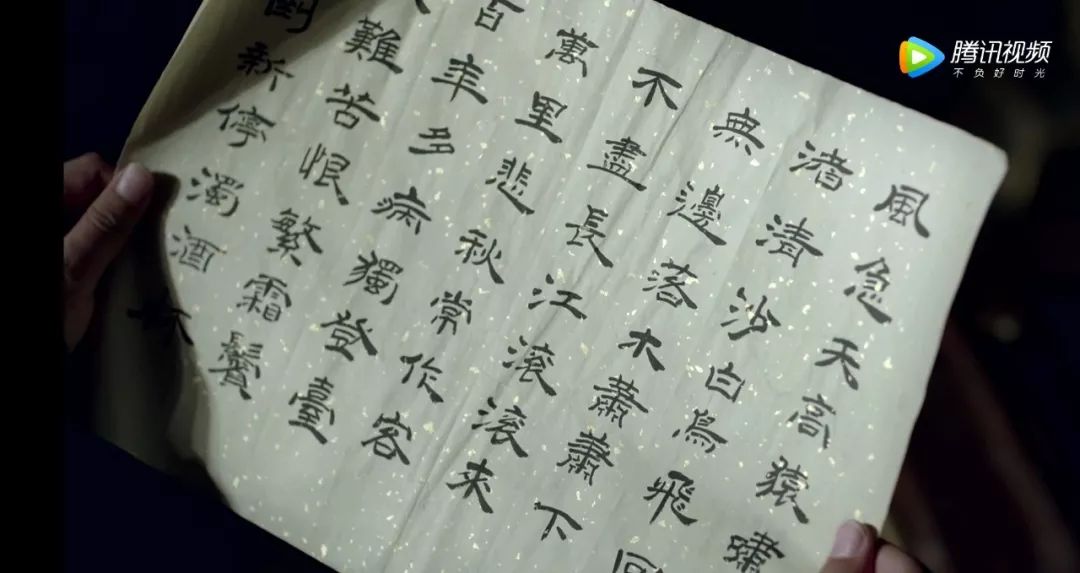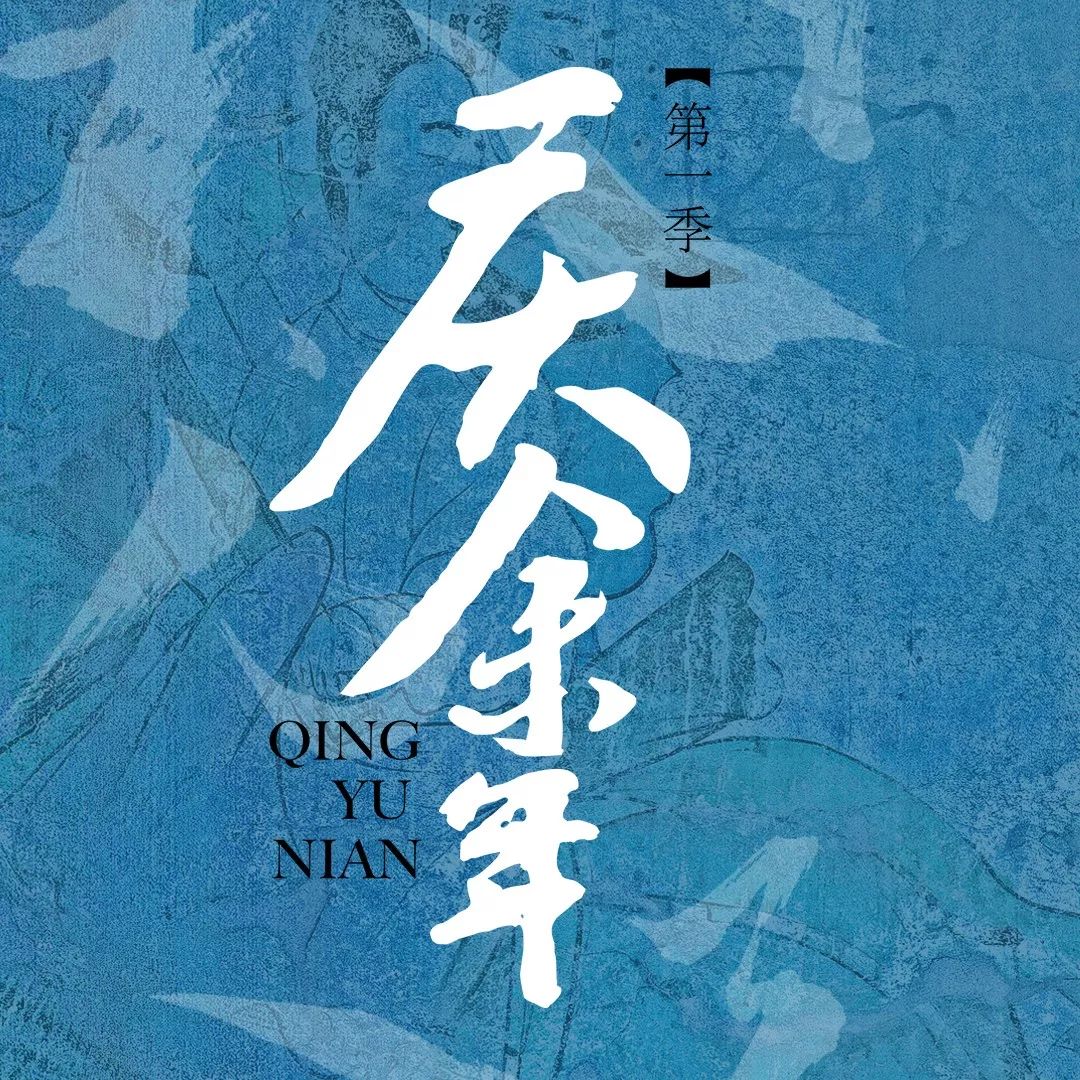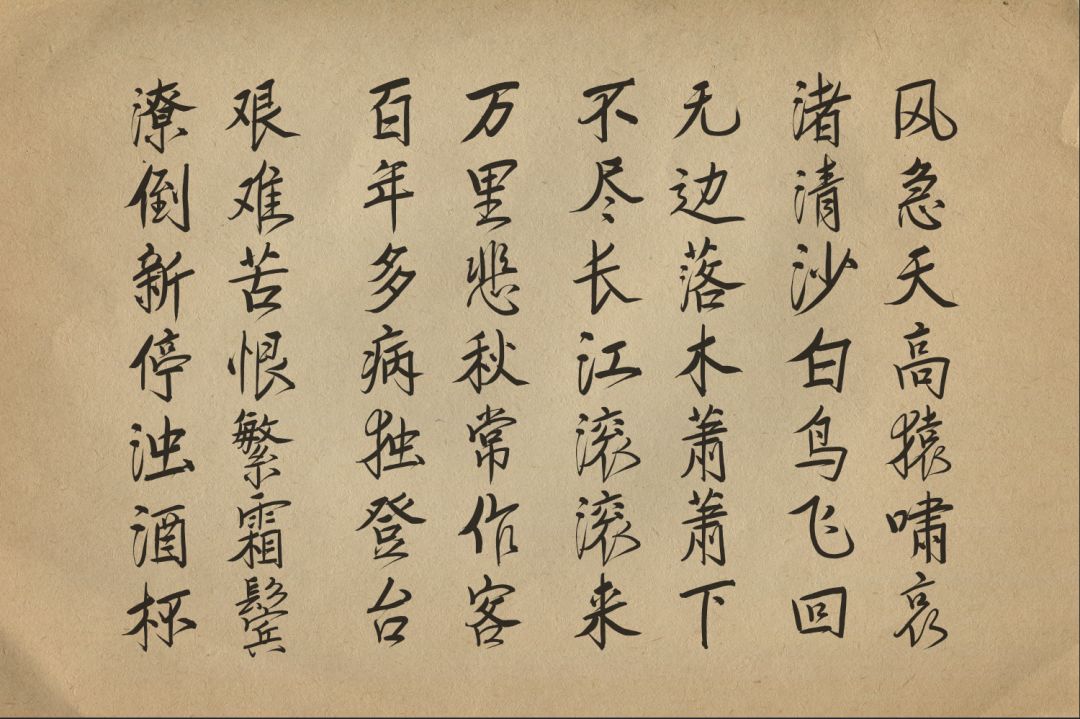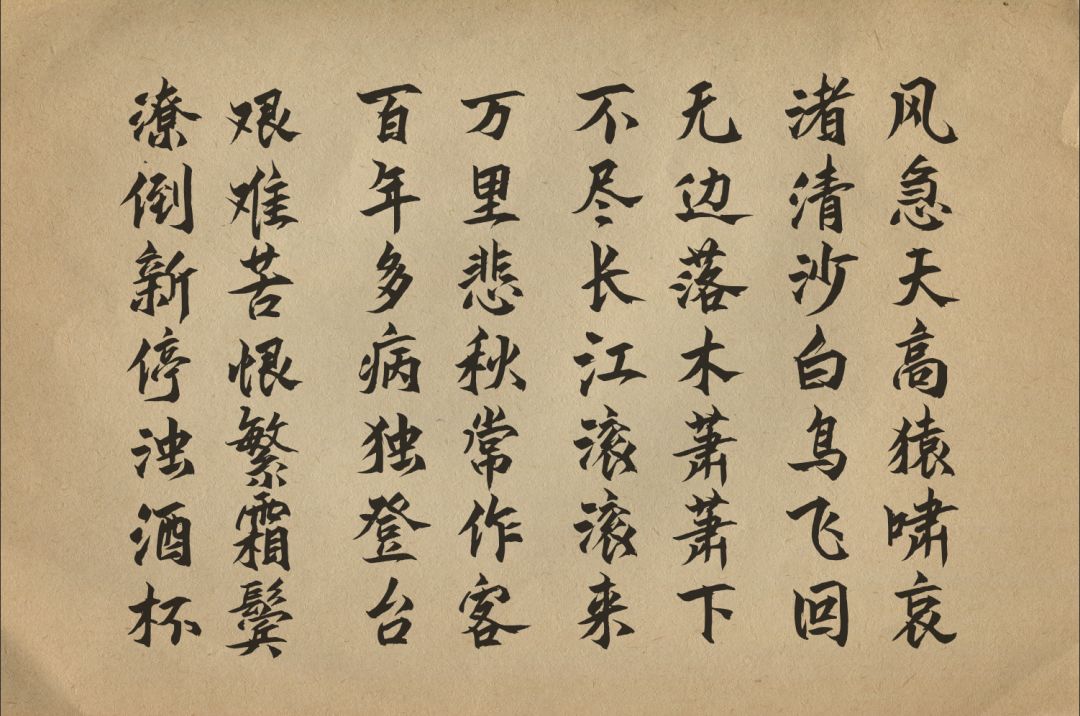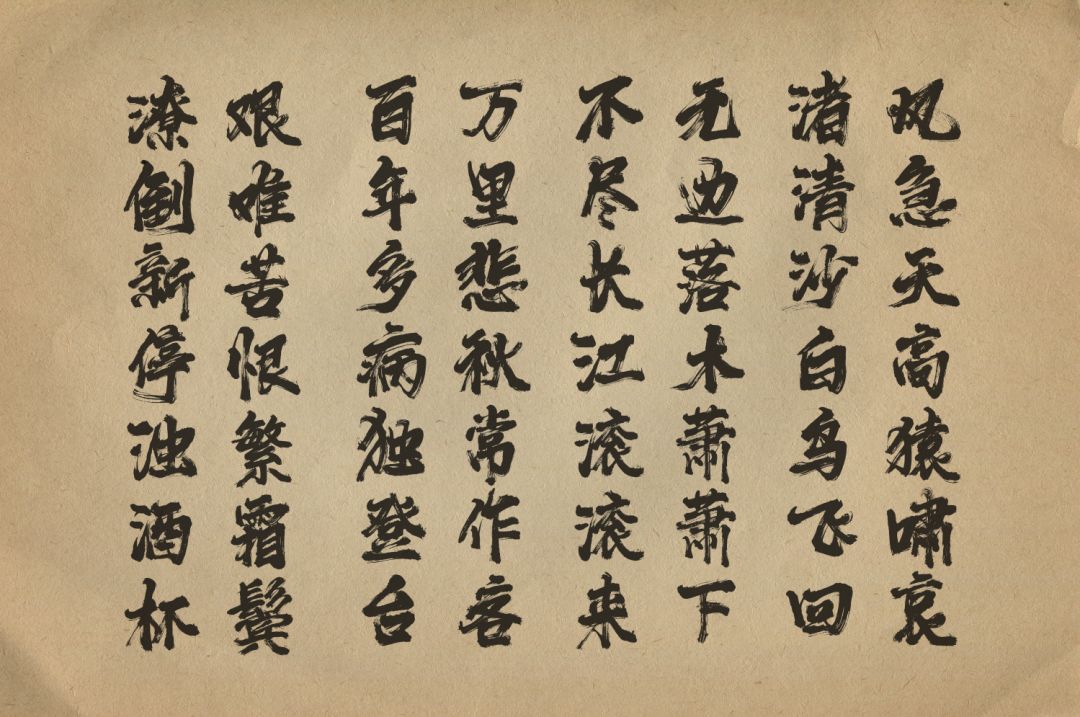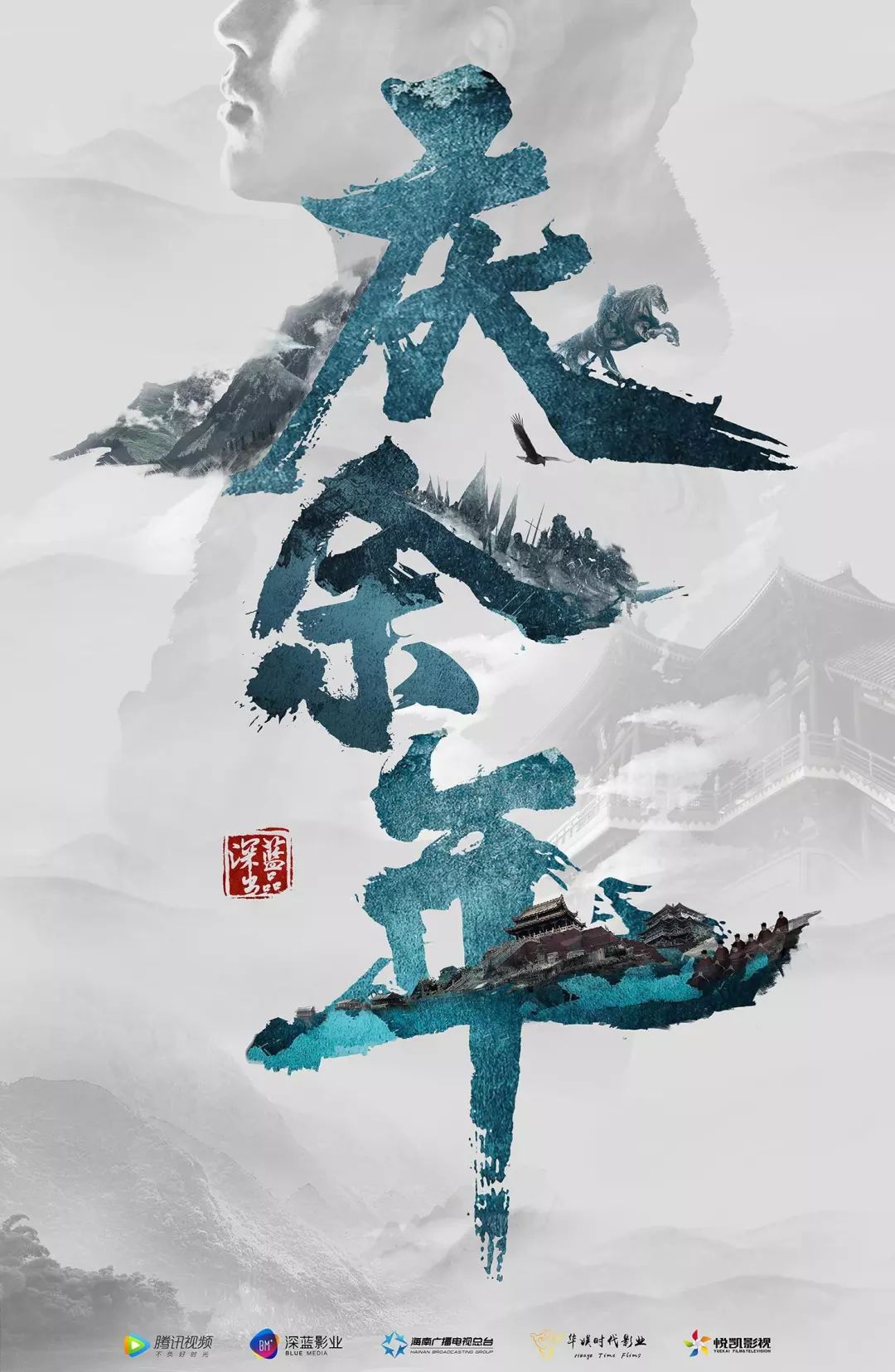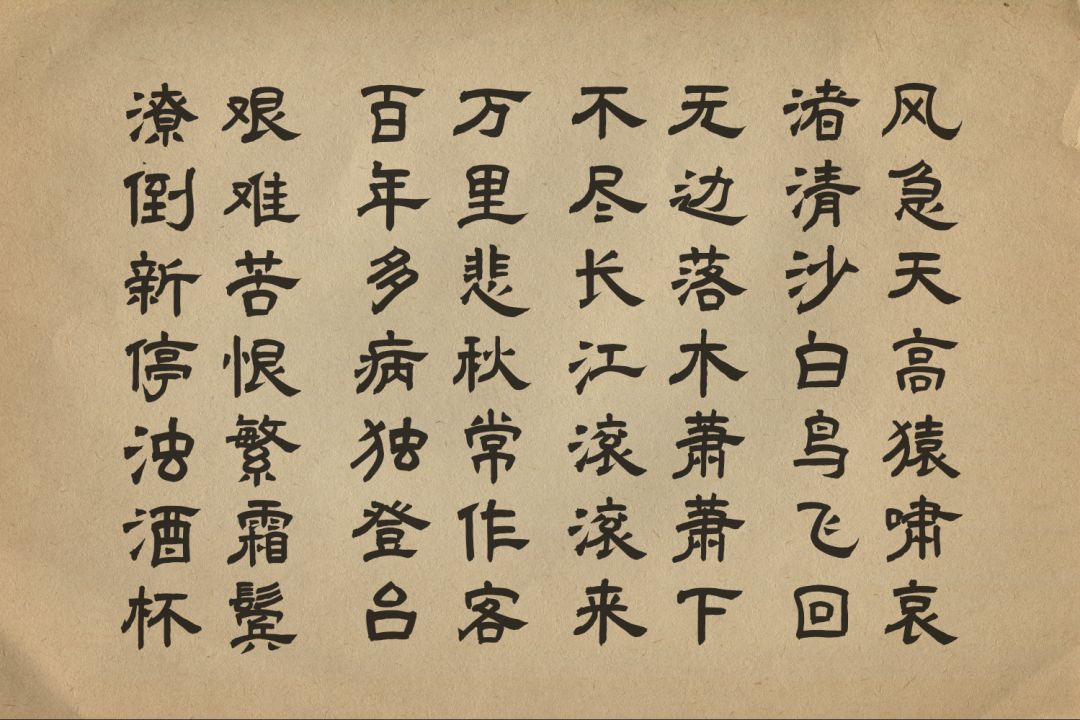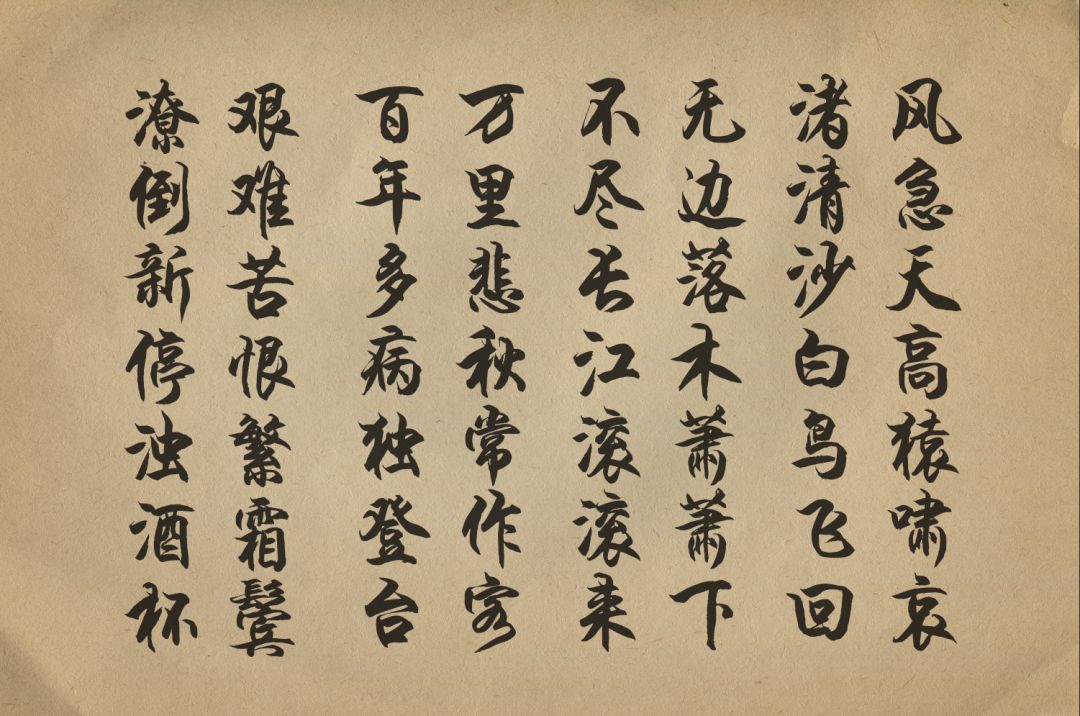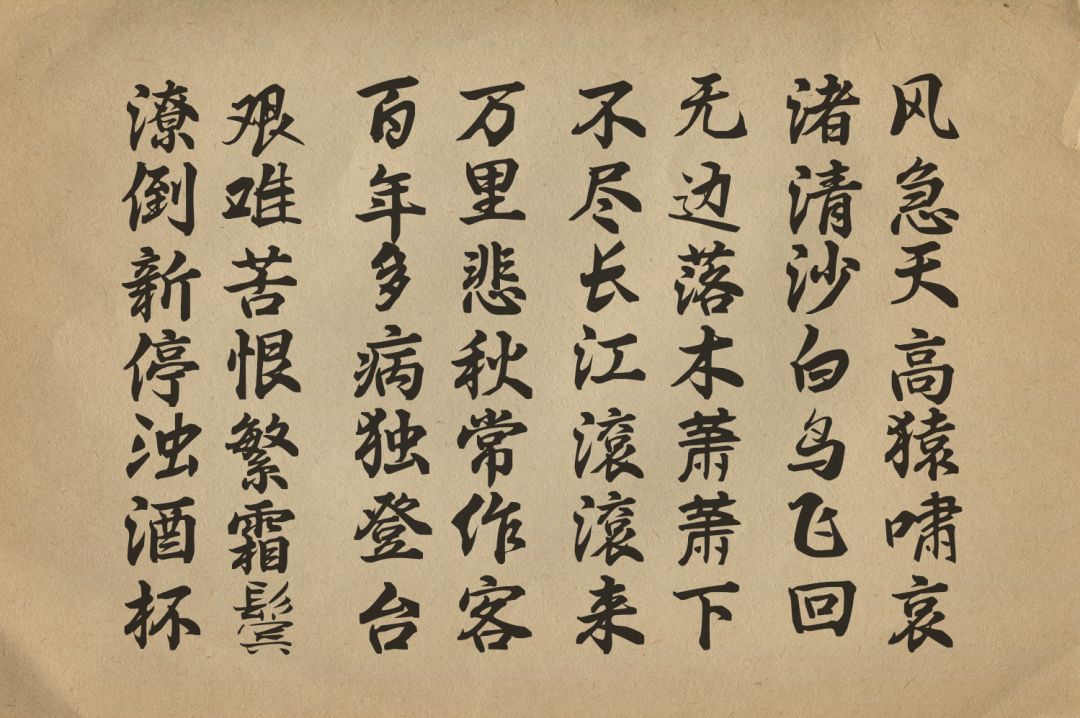
《庆余年》:反其道而行之,到底有多香?
这个周末,柚子恶补了最近大火的《庆余年》,实力演绎了什么叫香得不行!
不过这么好看的剧,刚开始却没隔壁《鹤唳华亭》声势浩大,还是张若昀的一条热搜,让我盯上了它。
按常理来说,找字替应该是主演写得不好,但看了剧情才知道,是不够丑……
一个拥有现代人思想和灵魂的人,怎么能写得一手好看的毛笔字呢,不科学不科学。
但终究为了要到皇室那好看,所以就成了模范版的《登高》。
但幸亏婉儿拿到的是原稿,而不是模范版,不然范闲就不能“字证清白”了。‍
所以有时候不管是人,还是字,都要有点辨识度……
说到这里,千万不要学小范大人写字,毕竟人家有霸道真气,哈哈哈!
你可以用你的字由真气,打出一手好字~
▲汉仪秦川漫书
▲汉仪彦湖手书
▲叶根友离贤行书
▲汉仪古隶
▲汉仪雪君体
▲Aa马上行楷
跟搞笑的字相对的,是《庆余年》海报上的字,一款霸道!
一款古风~
▲@早稻ZAODAO
用做倒计时海报,很有意境~
用做人物海报,也是很有余味。
▲起范了
▲我忘了
▲饭碗夫妇
▲父子?
▲言冰云快出来
柚子也特意找了类似的字体,你可以去玩玩~